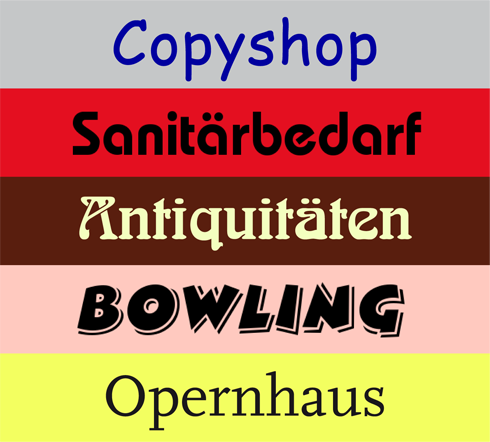
Es gibt Berufszweige, die gerne auf die immer gleiche Schrift zurückgreifen: siehe Branchenschriften und Branchenschriften (2). Zur Lieblingsschrift der Print- und Copyshops hat sich die Comic Sans gemausert, wahrscheinlich, weil sie billiger als eine A4-Kopie ist, nämlich kostenlos. Durchaus passend für die Berufsgruppe Gas-Wasser-Sanitär ist die Bauhaus, deren Buchstaben wie Siphons und Leitungsrohre gebogen sind. Der Klassiker im Antiquitätenmarkt ist die Jugenstilschrift Arnold Boecklin. Dem Fontblog-Leser passant verdanken wir den Hinweis auf die Schrift Bertram für das Bowlingcenter am Rande der Stadt, aber auch Spielzeugläden. Opernhäuser schmücken sich, wahrscheinlich wegen des Schriftnamen, zunehmend mit FF Scala. Wer kennt weitere Branchen, denen es an typografischer Imagination mangelt? Bitte Kommentar mit Bild …
Bäckereien aller Art (und inzwischen auch immer mehr Gärtnereien) scheinen die Cooper Black zu lieben, ich hab aber im Moment leider kein Bild zur Hand.
Ich muss erwähnen, dass Comic Sans auch auf unzähligen Arbeitsblättern von Lehrern zu finden ist. Möglicherweise soll dies eine Tafelanschrift imitieren… Was mich stante pede zur Unsitte einer separaten Druckschrift in den Vorgaben für Grundschüler bringt, anstatt diesen echte Buchschriften anzubieten, aber das ist ein anderes Thema.
Schwedische Möbelverkäufer sollen die verdana lieben. hab ich gehört ;)
“Bank Gothic” hat sich mittlerweile zum Gradmesser zwischen ernstzunehmenden Architekturwettbewerbsbeiträgen und unausgegorenen Schnellschüssen entwickelt. Erleichtert den ersten Rundgang.
Letztere beschriften ihre Präsentationen und Beiträge gerne mit “Bank Gothic”.
(Normalerweise gibt sich das zwanghafte Pläne-in-Bank-Gothic-Beschriften unter Architekturstudenten ab erreichen des Hauptstudiums…)
AvantGarde ist sehr beliebt bei Produktdesignern :-)
Slipstream für alle Transporteure.
Also Comic Sans für Copyshops halte ich für ein Gerücht. Mag sein, dass es da die eine oder andere Geschmacksverirrung gibt, aber die Mehrheit der Copyshops nimmt eine Fette Serifenlose.
siehe z.B. dieser Copyshop
Hat die noch keiner aufgeführt? Die Futura light in versal für Frauenzeitschriften und Kosmetik?
Beispiel: Amica
Erst durch Sachen wie Spiekermanns Typomania in den 80ern alle für Schrift sensibilisieren wollen und sich dann wundern, dass nicht alle Laien mitziehen. Ich denke jeder Berufszweig hat diese Nerdwitze wie hier, ich finde, dass die Beispiele weder der Wahrheit entsprechen noch kann ich lachen. Soll der Bäcker etwa Fontshop Kunde werden? Netter Versuch …
das problem ist weniger eine sache mangelnden interesse an typografie als ein problem des zuviels an interesse. vor 100 jahren hat jeder eine ordentliche schrift auf seine scheibe gemalt bekommen – gerne oben, über dem schaufenster, in gold auf schwarz – und alle läden sahen ungefähr gleich aus. das grafische bild unserer innenstädte hatte damals ein wesentlich höheres niveau. heute ist alles mit diesen logo-versuchen zugemüllt.
>heute ist alles mit diesen logo-versuchen zugemüllt
Motto!
speditionen/reiseunternehmen/verkehrbetriebe
verwenden gerne: antique olive
handwerksberufe wie dachdecker, maler und klempner verwenden natürlich auch gern helvetica (extended) und futura (black condensed). interessant finde ich auch, wie schon in den beispielen angedeutet, die farbgebung. dachdecker = schwarz/rot
gas-wasser-getöns = blau/rot
maler = rot/gelb/blau
bank gothic und copperplate sieht man oft bei steuerberatern.
cloister black und freunde sieht man oft bei tätowierern. Viking und American Uncial (neue hammer unical) für alles was mit mittelalter oder irland zu tun hat (irish pub).
broadway = theater
brush script = (italienische) eisverkäufer
pump triline = sportgeschäfte
stencil = waffen- und militärgeschäfte
ich könnt endlos so weitermachen ;)
genau britta, einfach auswürfeln!
ich glaub ich werde mal ein tool entwerfen, ähnlich einer wählscheibe oder einem glücksrad. da kann man dann an einem rad drehen auf dem diverse branchen stehen und ein zweites rad, welches die ‘spaßfonts’ abbildet, bewegt sich entgegengesetzt. beim stillstand des rades zeigt dieses gleichzeitig die farbkombination für die jeweilige branche mit an.
die ergebnisse könnten so aussehen:
sportgeschäfte = arnold boecklin (rosa/schwarz)
bäcker und back-shop = pump triline (blau/rot)
theater und opernhäuser = comic sans (grün)
bioläden = bauhaus (rot/blau/gelb)
architekten = betram (braun/beige)
ich glaub damit ich werd reich. :-D
zitat von #11:
>[...] vor 100 jahren hat jeder eine ordentliche schrift auf seine scheibe gemalt bekommen – gerne oben, über dem schaufenster, in gold auf schwarz – [...]
wichtiger punkt. selbst die schönste schrift kann in klebebbuchstabenglänzendem RAL 3000 auf plastikschild nur verlieren. aber vor 100 jahren war ein laden auch gerne mal 20-30-40 jahre im selben ladenlokal, falls kein weltkrieg dazwischen kam. heute gehört die fassade dem vermieter und der überlässt dem mieter 5 schraubenlöcher für sein ladenschild.
die visuelle vermüllung der städte geht einher mit der erfindung der klebefolie…
Das Problem ist vielleicht aber nicht automatisch mit zu-viel-Design zu übersetzen, sondern eben mit zu viel SCHLECHTEM Design. 90 % von allen, danke lieber Theo Sturgeon, ist eben Scheiße. Gilt auch hier.
Wobei Straßenwerbung auch cool sein kann, wenn man nur groß genug denkt: